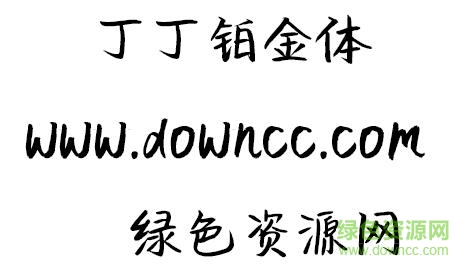
丁丁鉑金體文件擁有猶如鉑金一般的字體樣式,讓你在使用的時(shí)候感受到不錯(cuò)的字體使用體驗(yàn),這款字體在各類(lèi)行業(yè)中使用都能夠帶來(lái)很好的影響和效果,快來(lái)綠色資源網(wǎng)下載吧!
讓你在使用這款字體的時(shí)候能夠感受到濃濃的貴族氣息,用這款字體碾壓好友,還能夠在媒體制作中給觀賞者一種貴氣的視覺(jué)體驗(yàn)!